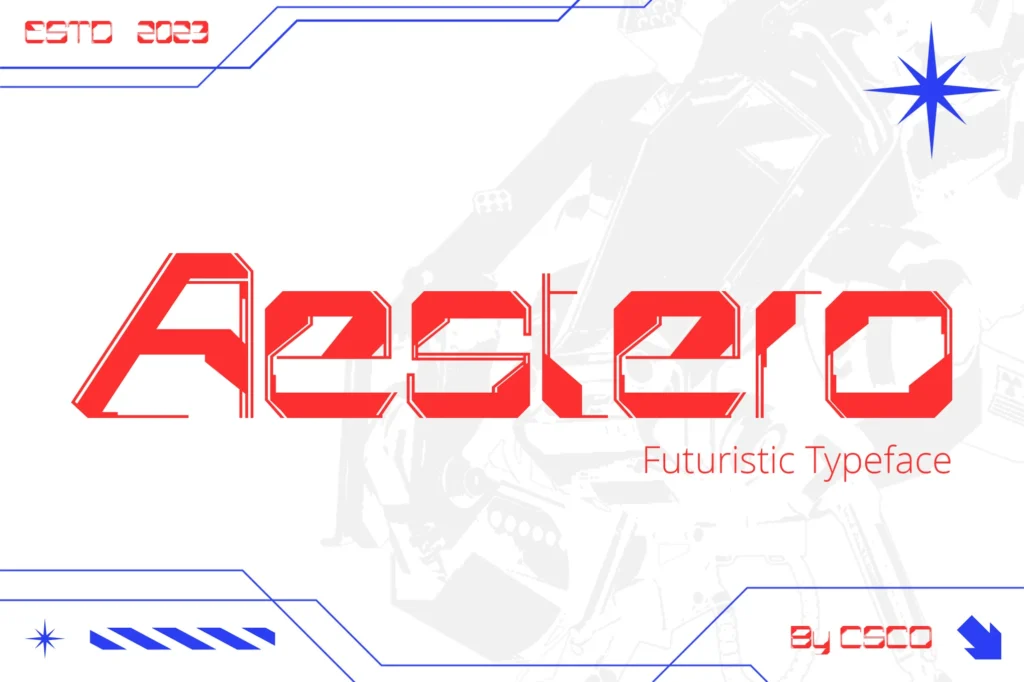
Parce que chaque projet graphique est unique et dépend de la sensibilité de son auteur, le choix de la typographie qui va le composer n’est parfois pas évident.
Si vous désirez inscrire votre travail dans le mouvement futuriste, sachez que plusieurs polices peuvent faire l’affaire, l’esthétique passant parfois après la beauté de la mécanique.
Afin de vous aider à prendre la bonne décision, voici donc une sélection de 12 polices d’écriture futuristes à télécharger sur Internet.
1. Gears of Peace (gratuite)
Créée par Scott Nuss, la typographie Gears of Peace est très appréciée des graphistes.
Il faut dire que lorsque ces derniers travaillent sur un projet en lien avec la science-fiction, ils tiennent là une police de caractères de belle qualité.
Futuriste mais restant facile à lire, elle est une référence.
2. Alexana (gratuite)
Conçue par le designer Marc Mora, la typographie Alexana est une typologie futuriste particulièrement agréable à l’œil.
Idéale pour illustrer un univers science-fiction ou un univers mystérieux, elle se compose uniquement de lettres majuscules sans accents. Elle est ainsi parfaite pour rédiger les gros titres d’un projet.
3. Space Age (gratuite)
Si votre création graphique invite à voyager dans l’espace ou nous plonge en pleine science-fiction, la police Space Age pourra être celle retenue pour votre projet.
Il faut savoir qu’elle se base sur la police utilisée pour l’attraction “Mission : SPACE” située dans le parc Epcot de Walt Disney World Resort.
4. Spin Cycle (gratuite)
S’intégrant parfaitement à toute création contemporaine et particulièrement adaptée à l’univers des nouvelles technologies et du jeu vidéo, la typographie Spin Cycle est une police de caractères sans sérif.
Elle a la particularité de combiner des lettres orientées tantôt vers la gauche et tantôt vers la droite, ce qui lui confère un look original.
5. Crysis Bold (gratuite)
Tirant ses origines du célèbre jeu vidéo éponyme, la typographie Crysis Bold ne passe pas inaperçue et pourra avoir tendance à prendre le dessus sur les éléments d’arrière-plan.
Il faut dire qu’elle est une police futuriste “engraissée” et donc imposante.
6. Quantum (gratuite)
Conçue par Greg Seso Ortiz, la typographie Quantum est à la fois audacieuse et futuriste et convient parfaitement pour des projets de création graphique dans l’univers des jeux et des loisirs.
Assez massive, cette police donnera du caractère à vos réalisations.
7. Perfect Dark BRK (gratuite)
Dans l’univers des nouvelles technologies, de l’automobile ou même de l’architecture, il peut arriver qu’on veuille exprimer à la fois la puissance et le futurisme.
Eh bien, Perfect Dark BRK est la police qu’il vous faut si c’est l’objectif que vous désirez atteindre.
8. Vindemia (payante)
Allant droit au but, la typographie Vindemia conviendra pour tous vos projets graphiques futuristes.
Elle mérite d’être combinée avec de beaux graphismes puisqu’elle a l’avantage d’être élégante mais de ne pas éclipser les éléments au second plan.
9. Tokyo (payante)
Envie de donner un style japonisant à votre projet graphique, la typographie Tokyo devrait vous séduire.
En effet, cette police futuriste d’inspiration nippone conviendra parfaitement pour des travaux autour des nouvelles technologies.
10. Etheriq (payante)
Si elle est souvent associée aux extra-terrestres et aux vaisseaux spatiaux, la typographie Etheriq semble aussi en mesure de convenir pour des projets d’architecture ou de mode.
Les ruptures de lignes dans les lettres de cette police lui confèrent un style minimaliste que les graphistes apprécient.
11. Cintra (payante)
Voilà une police sans empattement qui pourra se fondre dans n’importe quel projet graphique, sans pour autant passer totalement inaperçue car là n’est pas son objectif.
Facilement lisible, Cintra conviendra pour les titres, les sous-titres ou même les contenus de vos projets.
12. Robodron (payante)
Des courbes rondes et lisses et des arêtes bien marquées, voilà les deux caractéristiques majeures de la typographie Robodron.
Se démarquant très facilement de son arrière-plan, cette police convient parfaitement pour le logo d’une marque proposant des produits high-tech.
Comme vous pouvez le voir, il existe de nombreuses typographies à votre disposition pour réaliser des créations futuristes. Qui plus est, il ne s’agit là que d’une sélection et bien d’autres peuvent être trouvées sur Internet.